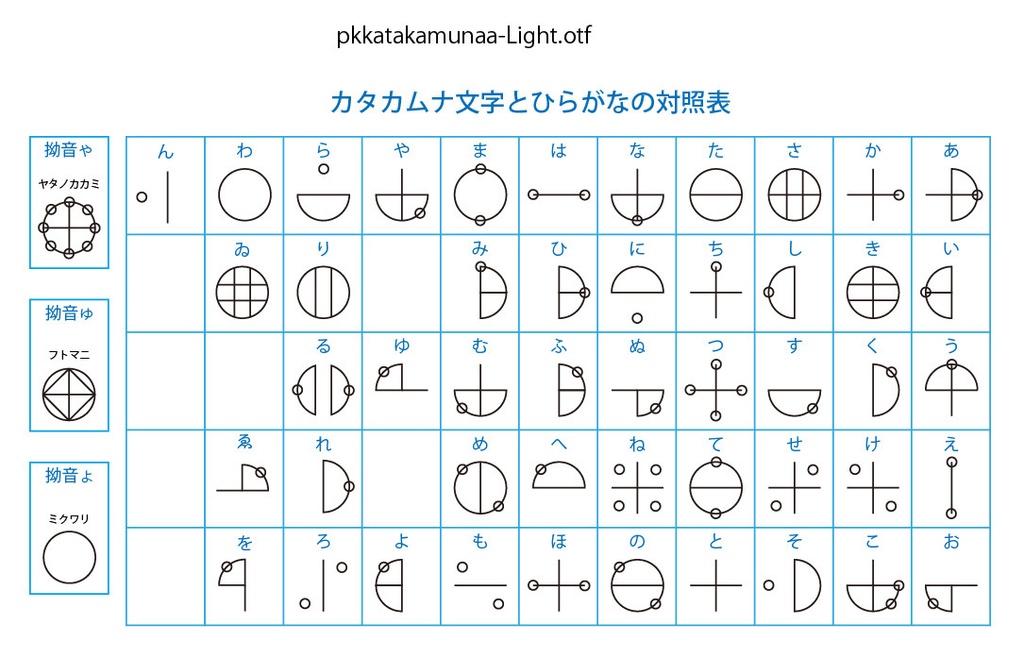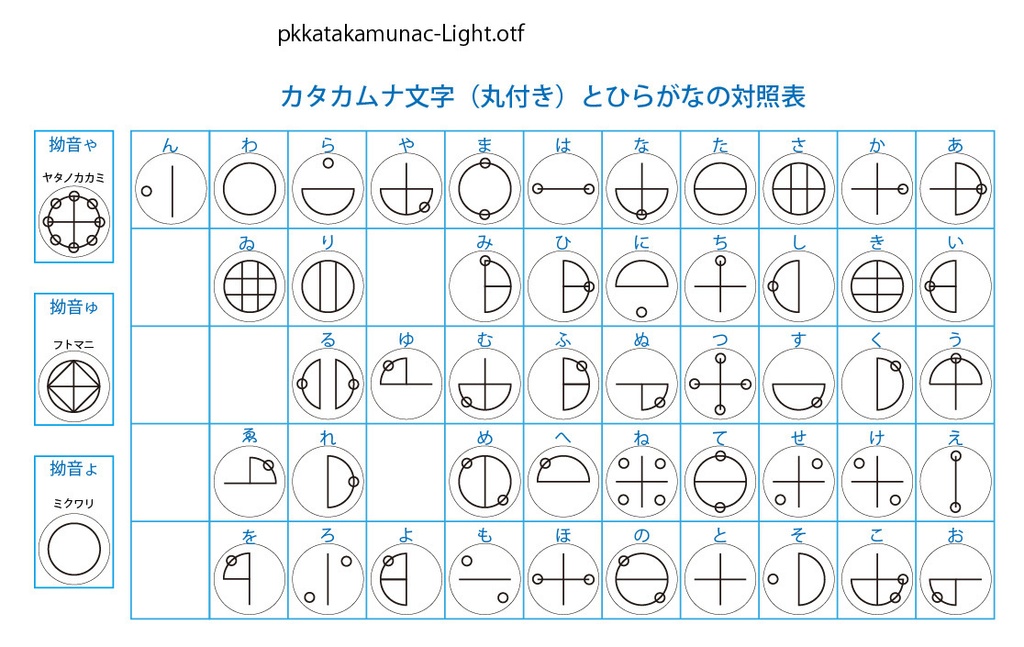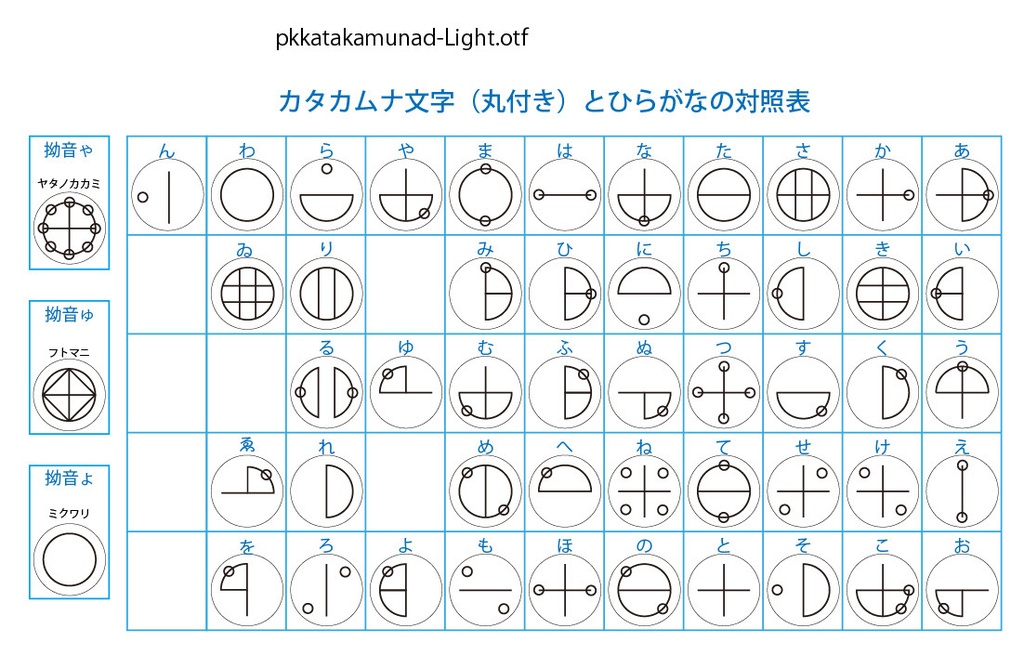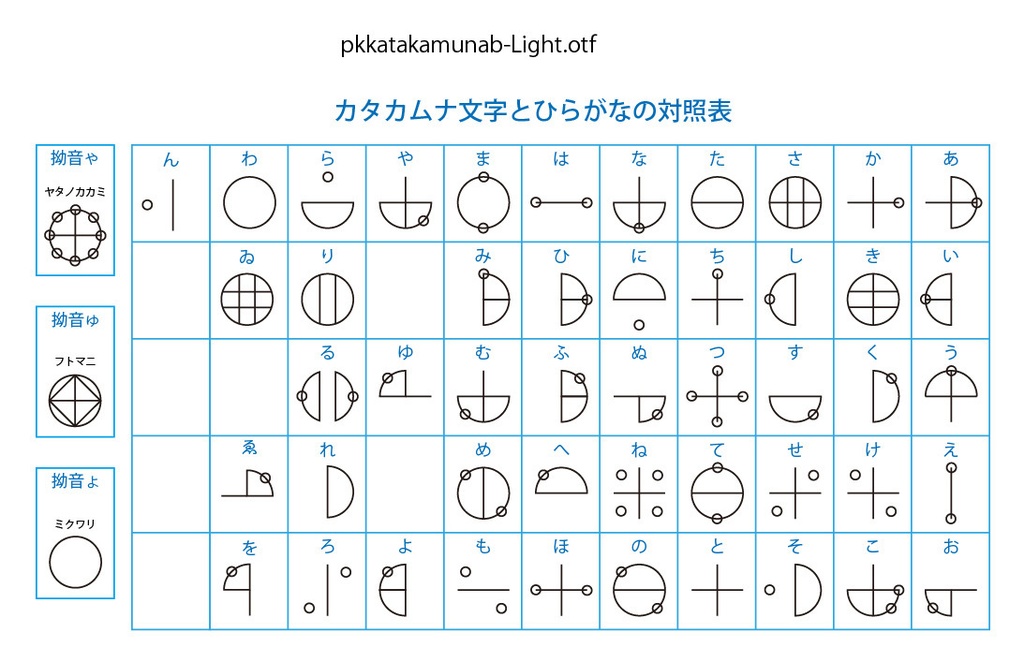
デジタルコンテンツ カタカムナ文字Lightフォント
カタカムナ文字のフォントです。 文字を丸囲みしてあるもの、丸囲みしてないものの2種類のフォントを同梱しました。 カタカムナ文字とは、実在不明の「カタカムナ神社」のご神体とされている書物「カタカムナノウタヒ」に使われている、円と直線の組み合わせからなる幾何学的図形の文字です。 1949年楢崎皐月(ならさきこうげつ)によって発見されたものとされており、「カタカムナノウタヒ」にはカタカムナ文字が渦巻状に並んだ、「ウタヒ」(歌)と呼ばれるものが80首書かれています。楢崎の解読によると、カタカムナ文字は日本語のかな48文字に対応するとされています。 ひらがな48文字(ゐゑ含む)を入力すると対応するカタカムナ文字が表示されます。 また、カタカムナノウタヒの中心図象として使われている3つの図象ヤタノカカミ、フトマニ、ミクワリも用意しました。 【収録文字】 ひらがな(あいうえおかきくけこさしすせそたちつてとなにぬねのはひふへほまみむめもやゃゆゅよょらりるれろわゐゑをん) ※ヤタノカカミ、フトマニ、ミクワリをそれぞれ拗音「ゃ」「ゅ」「ょ」に割り当てました。 【データ内容・使用方法】 zipファイルを解凍してください。 OTFファイル pkkatakamunaa3-Light.otf(丸囲みなし) pkkatakamunab3-Light.otf(丸囲みなし) pkkatakamunac3-Light.otf(丸囲みあり) pkkatakamunad3-Light.otf(丸囲みあり) JPGファイル(カタカムナ文字とひらがなの対照表) comparisona.jpg comparisonb.jpg comparisonc.jpg comparisond.jpg テキストファイル(このファイル) readme.txt が収録されています。 ご希望のフォントをインストールしてください。 【購入の際の注意点】 商用利用OKです。 使用した場合、ご一報いただけるとうれしいです。Twitterなどで紹介します。 フォントファイルの改変・再配布は禁止です。 ※追記 2021.9.20 丸囲みなしのほうのファイル名を pkkatakamuna1 から pkkatakamunaa に変更しました。 丸囲みありのほうに「ん」が抜けていたので追加しました。 Word、Excelでもフォントを選ぶ際にフォント名が表示されるようにしました。 ※追記 2021.10.2 「れ」の表記が資料により2とおりあり、どちらが正しいか判定できないため、従来のフォント(右半円に小円がついたもの)に加え、pkkatakamunab-Regular.otf(丸囲みなし)とpkkatakamunad-Regular.otf(丸囲みあり)を追加しました。こちらは「れ」の表記を右半円のみとしています。 ※追記 2023.2.4 文字の一部にミスがあったため、修正しました。 これより線幅の太いフォントを制作したため、こちらのフォントの名称を「カタカムナ文字Light」に変更しました。 ※2024.2.4追記 スペースが■に変換されていたのでファイルを修正しました。